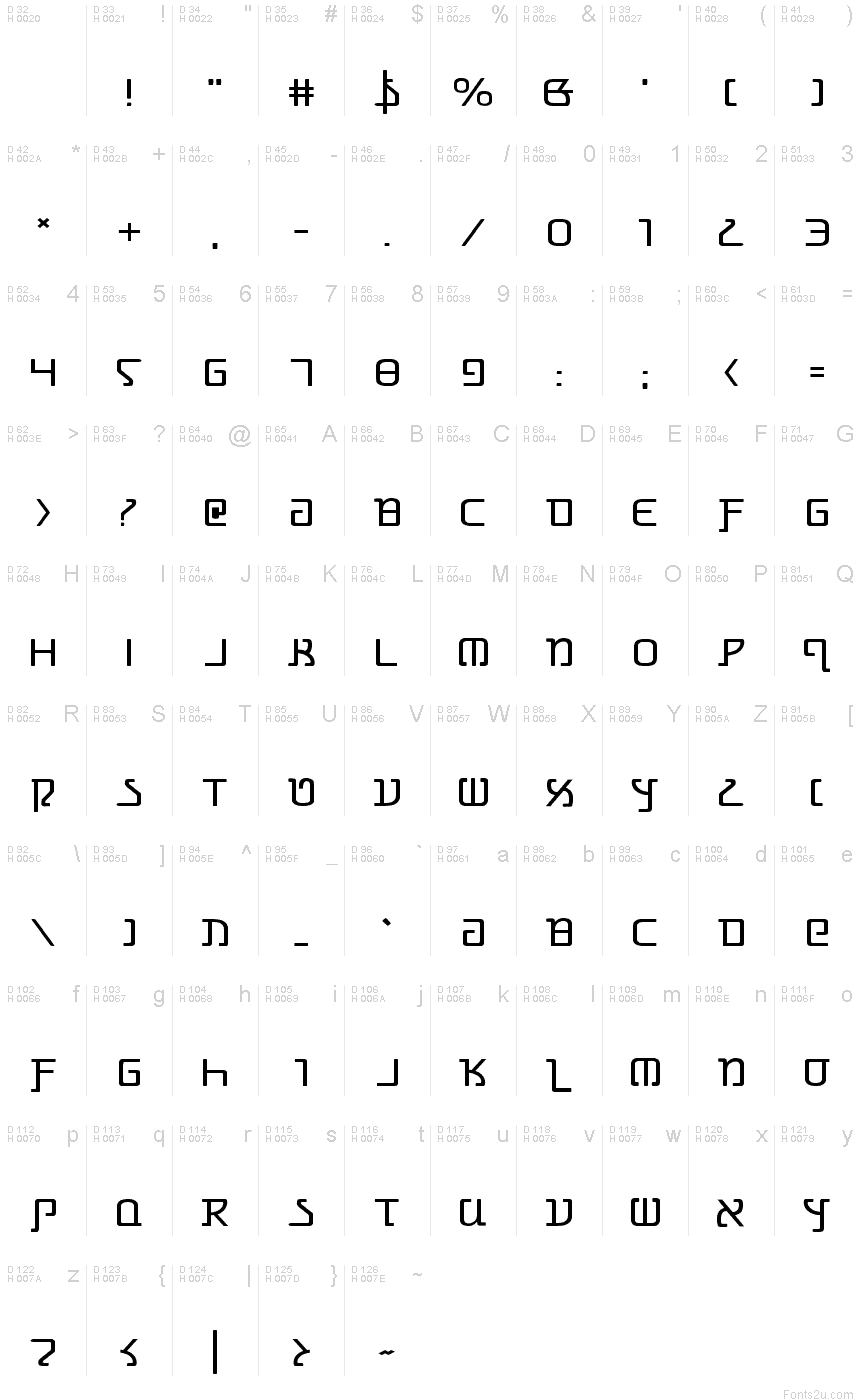
Grimlord Expanded od Iconian Fonts to darmowy, retrofuturystyczny krój pisma typu display, zbudowany z szerokich, kanciastych pociągnięć. Jego litery łączą zaokrąglone zewnętrzne narożniki z gwałtownymi cięciami i wąskimi wewnętrznymi szczelinami, co przywodzi na myśl tytuły z filmów science-fiction oraz wczesny sprzęt cyfrowy. Sylwetka jest surowa i mechaniczna.
Projektanci pracujący przy grach i muzyce elektronicznej uznają go za odpowiedni do ekranów tytułowych, okładek płyt i merchandise. Szerokie, segmentowane formy łatwo łączą się z motywami obwodów, statków kosmicznych i przemysłu. W takich zastosowaniach oferuje chłodniejszą, bardziej techniczną alternatywę dla konwencjonalnego liternictwa w stylu retro.
Grimlord Expanded